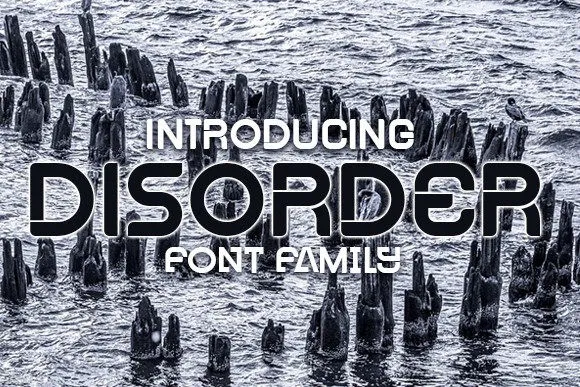
Disorder Font
Esta é uma fonte de exibição única perfeita para headlines grandes, marcas de logotipo, textos promocionais e gráficos publicitários. Ideal para criar logos únicos e atraentes, ou qualquer tipo de conteúdo que busque uma visão fresca em seu campo. Esta fonte totalmente maiúscula é perfeita tanto quanto o assunto lhe permitir. Especialmente adequada para ambientes onde a criatividade e a personalização são essenciais, esta fonte oferece uma maneira moderna de agregar valor às suas criações digitais ou impressas. Seja você um designer gráfico que busca trazer vida aos seus projetos ou alguém que está buscando dar um novo significado à sua marca através da tipografia, a Disorde Font pode ser o recurso ideal para você.